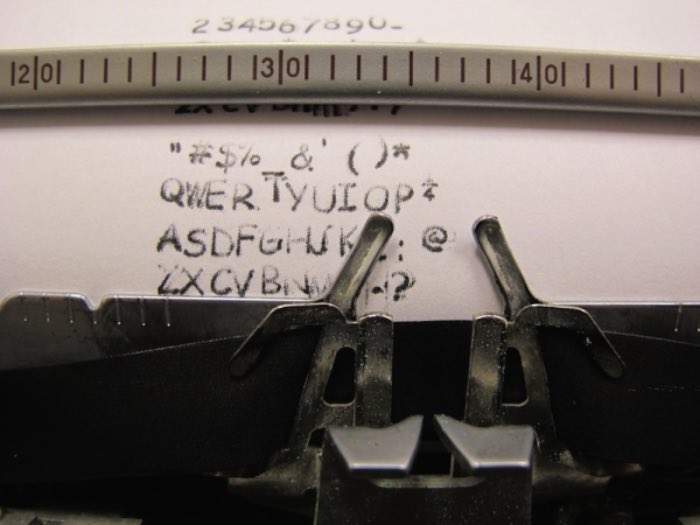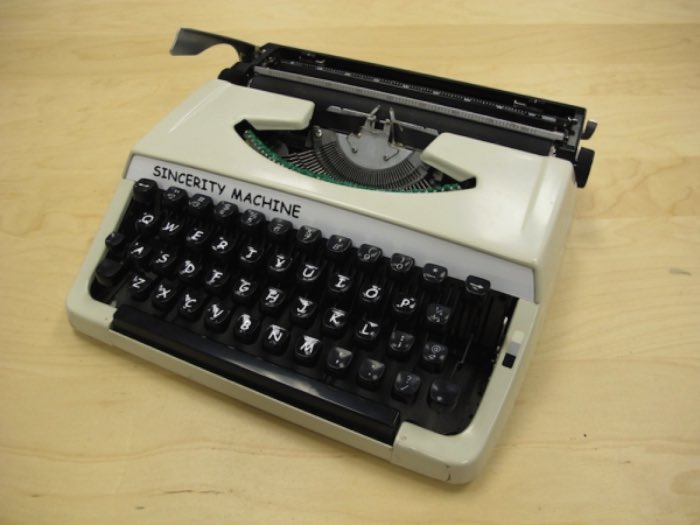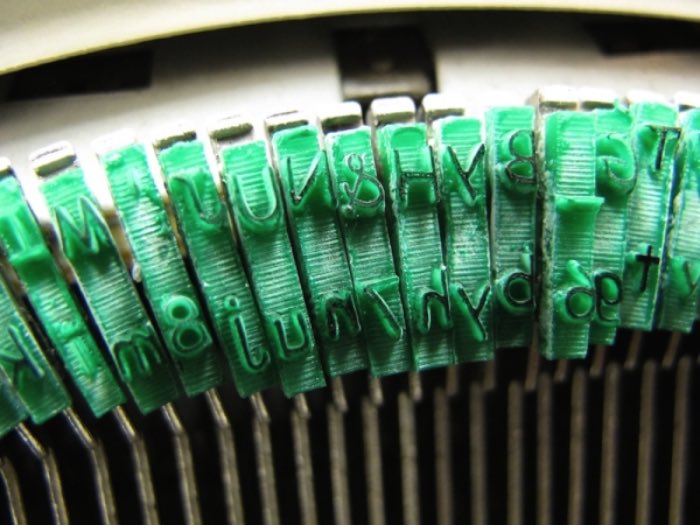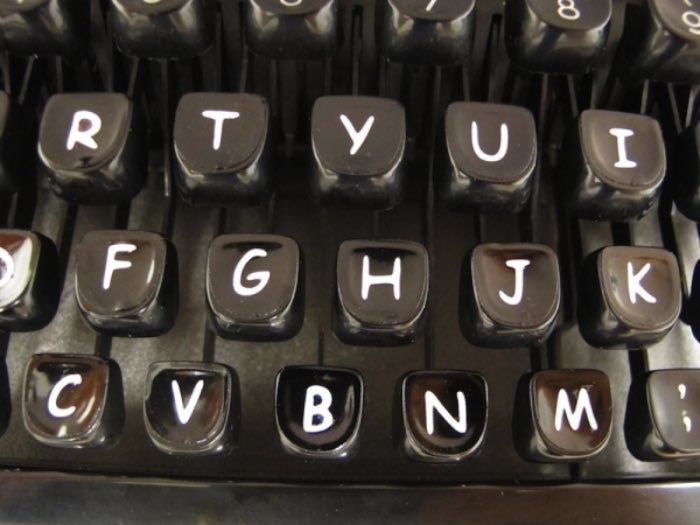
Sincerity Machine é o nome que essa máquina de escrever que datilografa em Comic Sans acabou recebendo. Sim, uma máquina de escrever em Comic Sans. Criação de Jesse England como parte de uma tese sobre como consumimos, criamos e guardamos mídia.
Mas, como que ele fez isso? Pelo que eu entendi, ele usou uma máquina de laser engraving para criar todo o alfabeto da Comic Sans em acrílico. Depois disso, colou essas pequenas placas tipográficas numa máquina de escrever modelo Brother Charger 11 e pronto. Dá para ver como ela funciona no vídeo abaixo.
As part of my ongoing thesis of questioning how we create, consume, store (and fetishize) media, it’s my wish that a classic, functioning typewriter altered to write in the most popularly despised font of modern times will provoke thoughts about such media concerns.
Acho interessante como que esse projeto foi desenvolvido e como que desenvolvemos um certo ódio tipográfico sem embasamento. Apenas pela repetição midiática. Não que eu esteja defendendo a Comic Sans mas tem coisas piores por ai, como a Papyrus.
Sincerity Machine: Datilografia em Comic Sans — Uma máquina de escrever em Comic Sans? É isso mesmo?